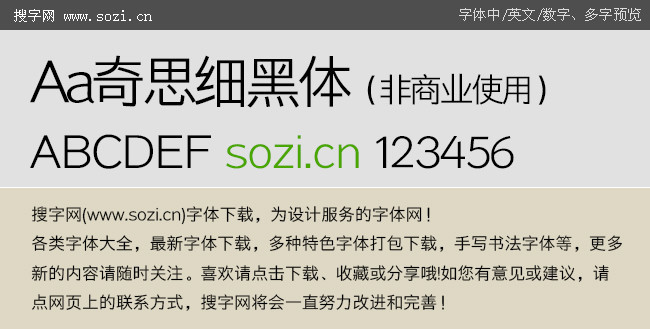
Aa奇思細(xì)黑體
搜字網(wǎng)給大家提供一款A(yù)a奇思細(xì)黑體(非商業(yè)使用)中文字體下載,該字體是一款簡(jiǎn)潔的黑體字體,字體簡(jiǎn)潔大方,結(jié)構(gòu)清晰,具有很好的視覺(jué)識(shí)別性,適用于平面宣傳設(shè)計(jì)、網(wǎng)頁(yè)設(shè)計(jì)、海報(bào)設(shè)計(jì)等應(yīng)用(此字體為個(gè)人非商用版,商用可以聯(lián)系QQ:1006760504)。